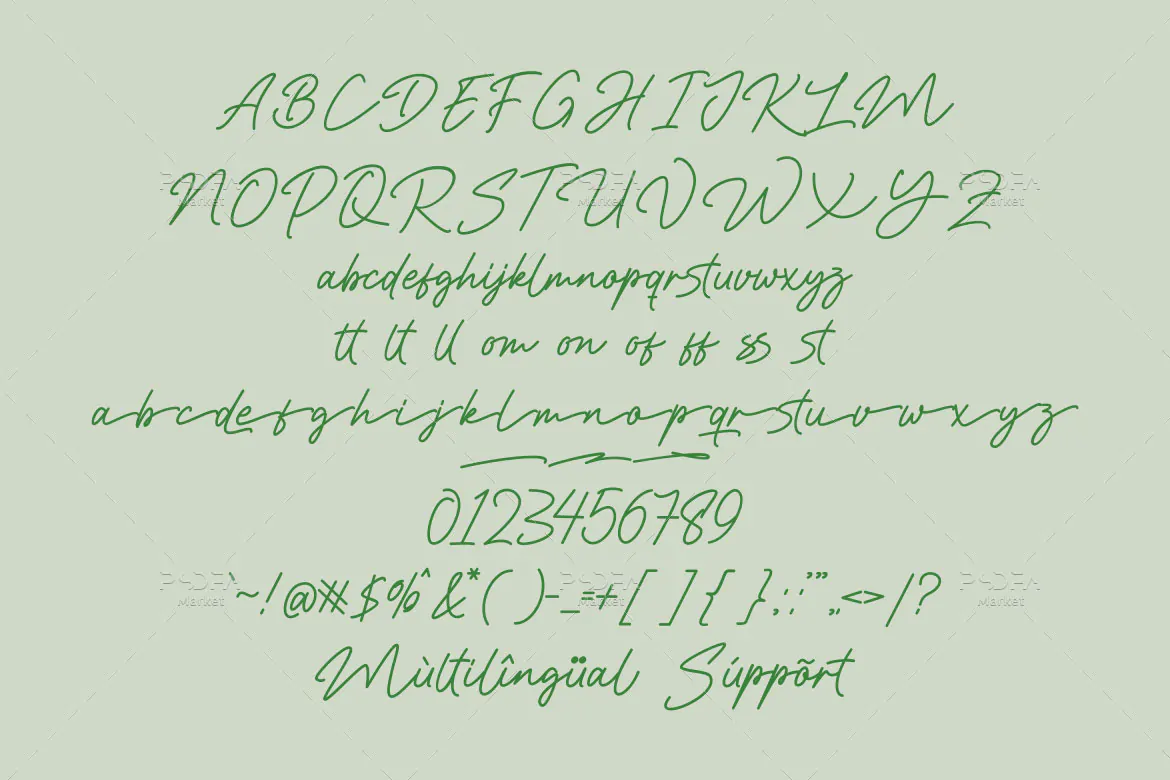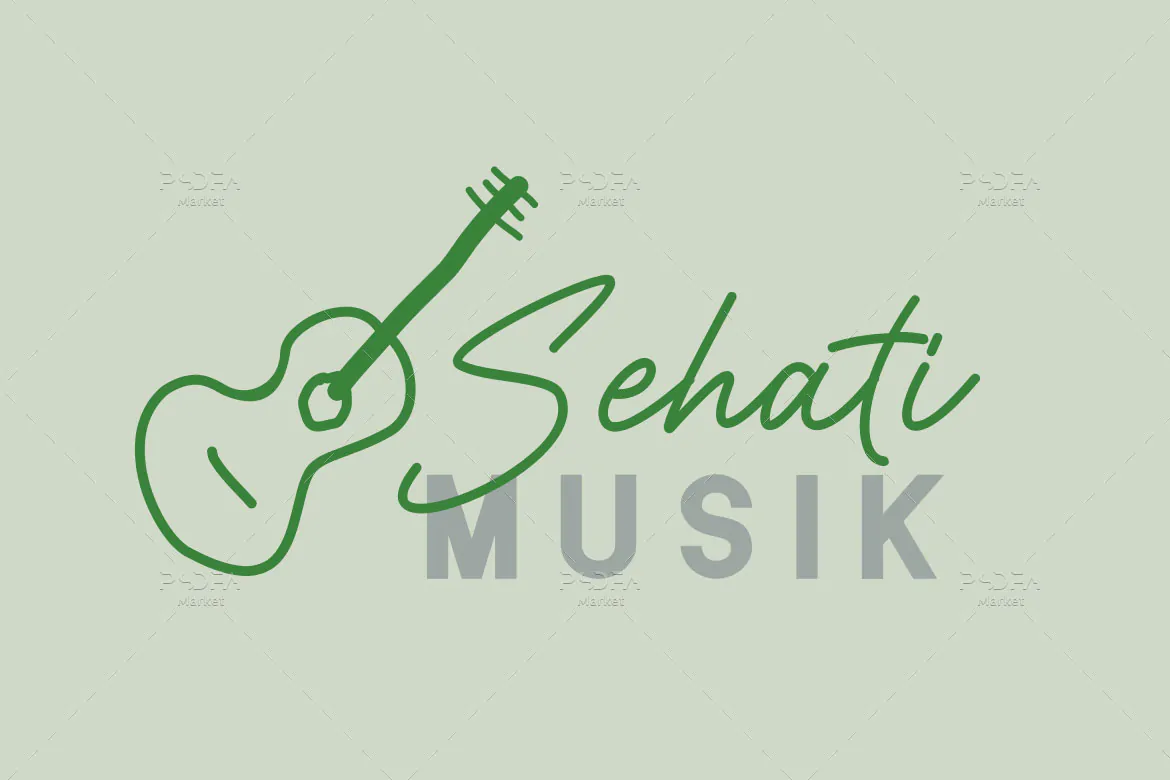
فونت سرهم نویسی باریک و نازک Bestien
فونت سرهم نویسی باریک
فونت سرهم نویسی باریک و نازک Bestien یک اسکریپت فونت انگلیسی زیبا است که مناسب جهت استفاده در طرحهای گرافیکی و نرم افزارهای مختلف میباشد. فونت با وزن معمولی طراحی شده است که میتوانید از آن در طراحی انواع پوستر، تراکت، تقویم، بسته بندی محصولات، آرایشی و بهداشتی، کارت ویزیت، بروشور و … استفاده کنید.